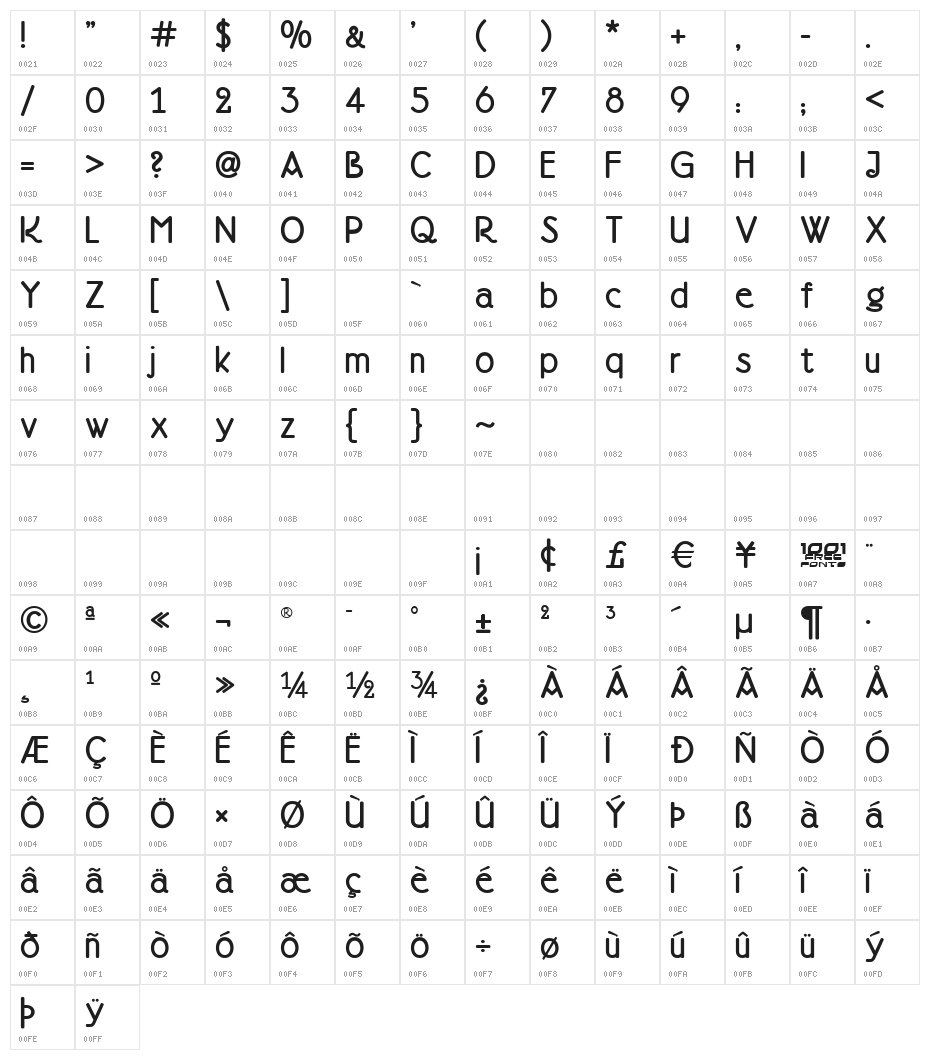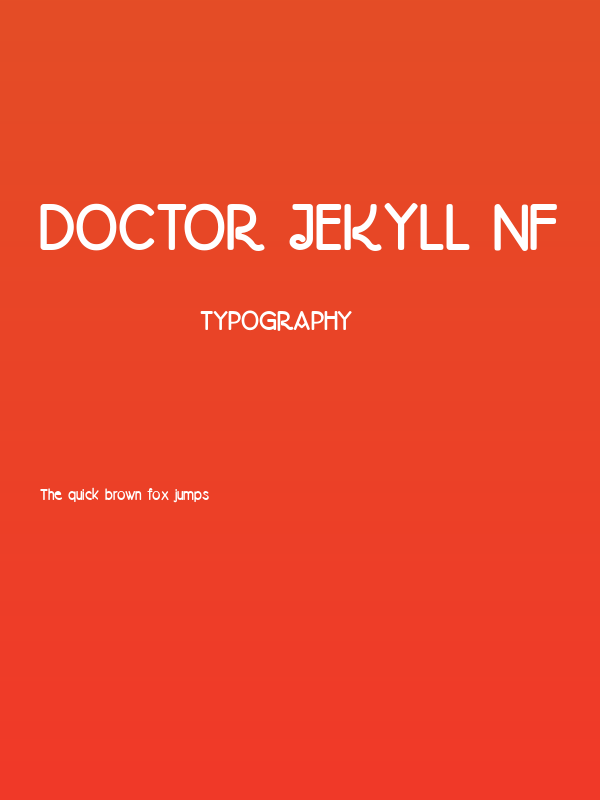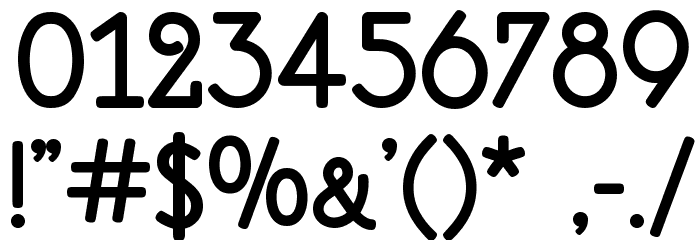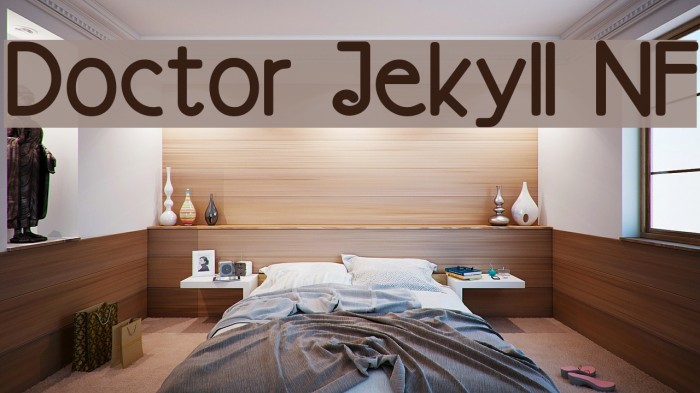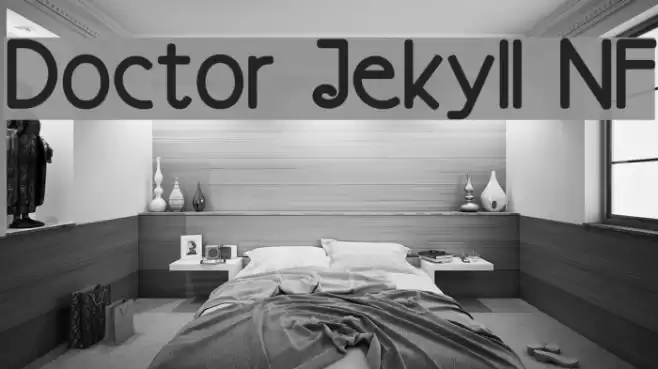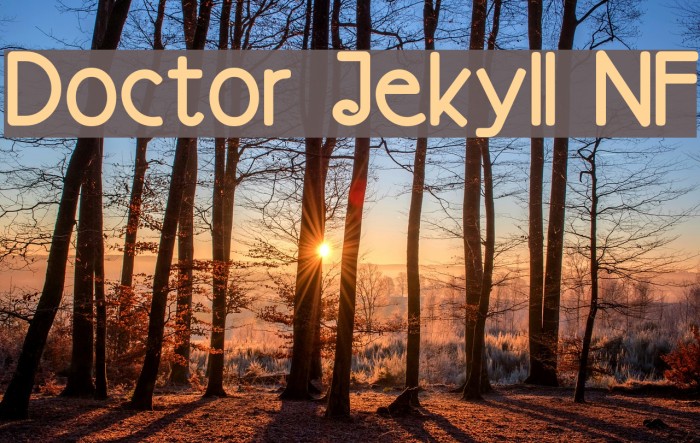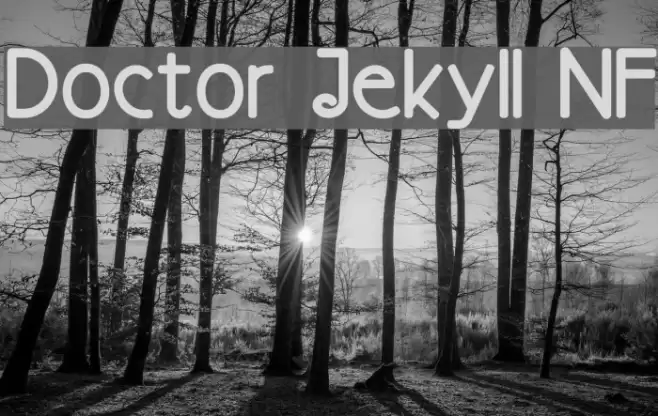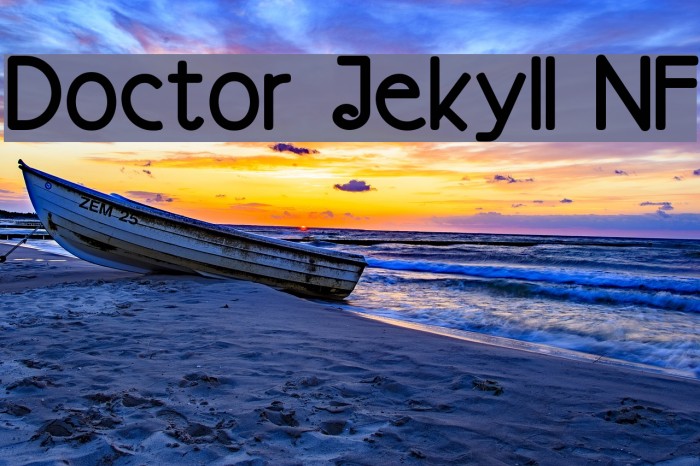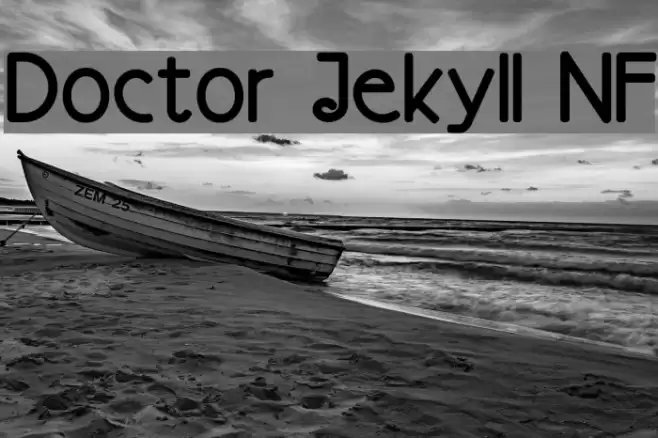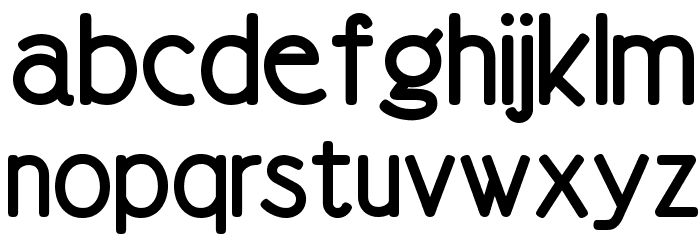
Doctor Jekyll NF Font
✎ Comic
| Projets proposés | Ideal for branding, advertising, children's books, and digital media where a friendly and modern look is desired. |